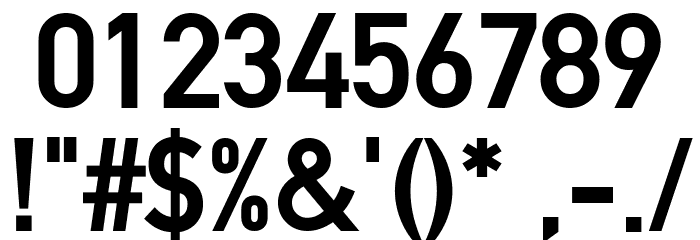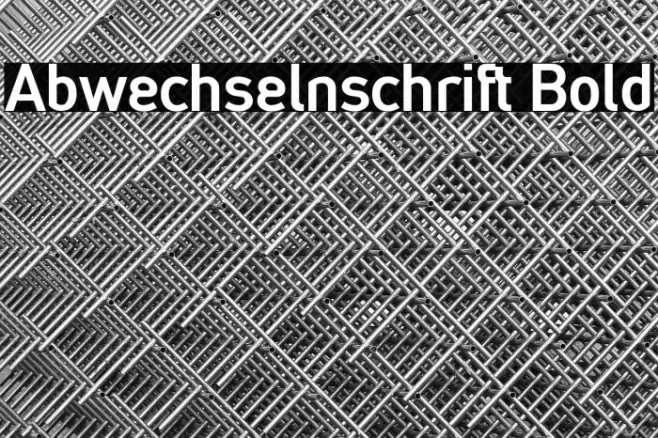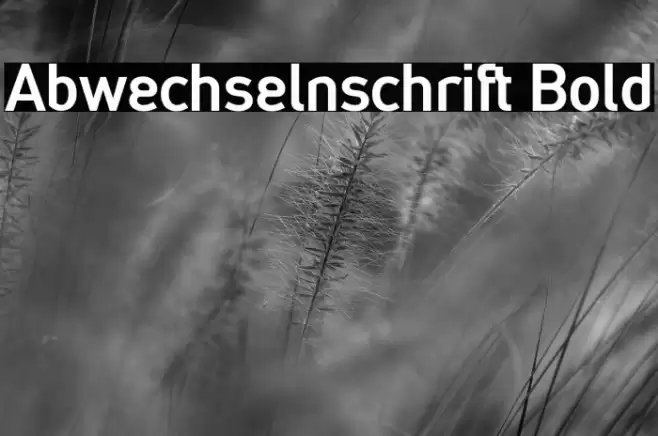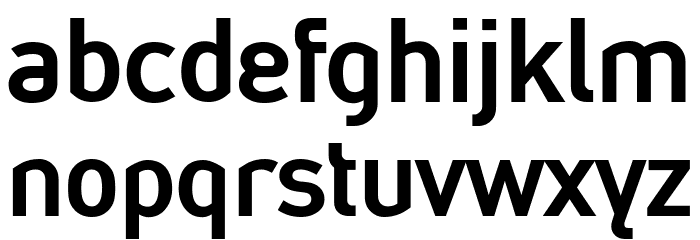
Abwechselnschrift Bold Font
✎ Sans Serif
| الاسم | Abwechselnschrift Bold |
| عائلة الخط | Abwechselnschrift |
| الفئات | Sans Serif |
| حالة الاستخدام | Headlines, Body text, Logos |
| مشاريع مقترحة | Ideal for branding, advertising, web design, and editorial layouts due to its clarity and modern appeal. |